4 font chữ tạo diện mạo đáng ngưỡng mộ cho website
Trong thời đại của công nghệ và tăng việc sử dụng các thiết bị di động, lựa chọn font chữ đã trở thành một khía cạnh quan trọng chủ yếu của thiết kế web.
Phông chữ có khả năng ảnh hưởng nhiều tới diện mạo và cảm nhận về một thiết kế. Tiếc là nhiều người không quan tâm đầy đủ đến việc lựa chọn chữ cho website, điều này có thể làm mất giá trị của ngay cả các thiet ke website được đầu tư nhất.
Suy nghĩ phổ biến của mọi người giống như kiểu: Tôi vừa tốn nhiều thời gian và công sức trong việc tạo nên cấu trúc tổng thể của một website, hình ảnh nào tôi chuẩn bị sử dụng và tông màu nào tôi chuẩn bị dùng đến...tại sao tôi lại cần tốn thêm công sức để chọn font nữa?
Sự khác biệt giữa một font chữ tốt và không tốt làm nên khác biệt đẳng cấp giữa một thiet ke website chuyên nghiệp và nghiệp dư.
Dưới đây là danh sách 4 font chắc chắn sẽ giúp mang lại diện mạo đáng ngưỡng mộ cho thiet ke web của bạn. Nhũng font chữ tuyệt vời này đã được sử dụng bởi nhiều chuyên gia thiết kế chuyên nghiệp. Bạn có thể tải những font chữ này ở link đi kèm và sử dụng nó cho sản phẩm của mình.
1. Open Sans
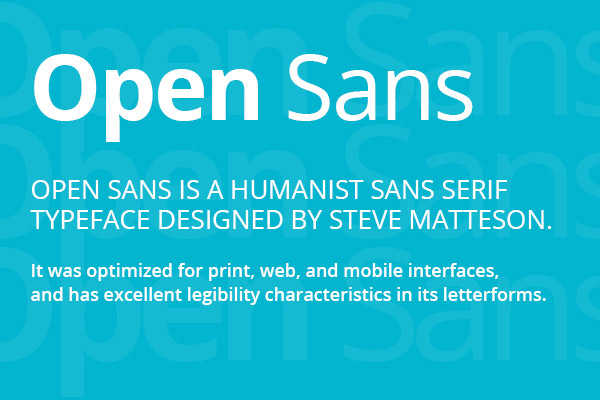
Font này được tại ra bởi Steve Matteson và nó có sẵn 10 biến thể. Phong cách đa dạng từ mỏng đến đặc biệt đậm nét. Font chữ khá đơn giản, gọn gàng và chuyên nghiệp.
Mặc dù font trông khá ổn khi ở kích cỡ to hơn hay nhỏ hơn nhưng tốt nhất hãy dùng nó ở dạng đặc biệt đậm là đẹp nhất.
Tôi muốn ám chỉ ở đây rằng phiên bản Open Sans Condensed cũng có sẵn ở 3 phong cách khác nhau. Toi nghĩ rằng phiên bản này có lẽ không phù hợp lắm với kích thước nhỏ, tuy vậy nhìn chung nó vẫn ổn với mọi trường hợp.
2. Oswald
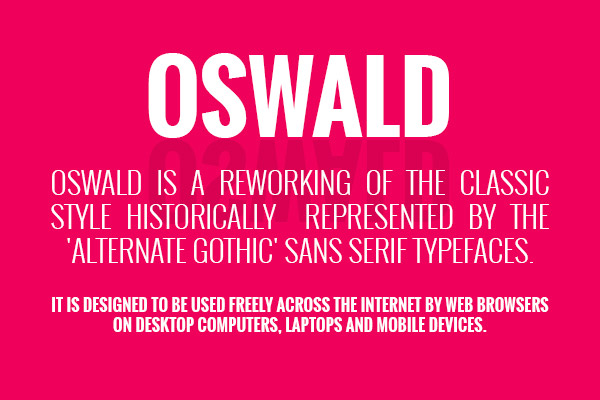
Oswald thuần túy là một font kỹ thuật số, nó đặc biệt được thiết kế để sử dụng cho các thiết kế web và thiết kế đồ họa trên mọi độ phân giải màn hình.
Đây là một phần của bộ font sans-serif, Oswald tiếp tục được cập nhật với các phiên bản được dùng trên website. Khoảng cách giữa các chữ nhỏ và nó rất hợp để làm chữ header.
Font chữ này nhìn khá gọn gàng cũng như hiển thị tốt trên các thiết bị duyệt web. Hãy cân nhắc đến việc dùng nó cho thiết kế web tiếp theo của bạn.
3. Lato
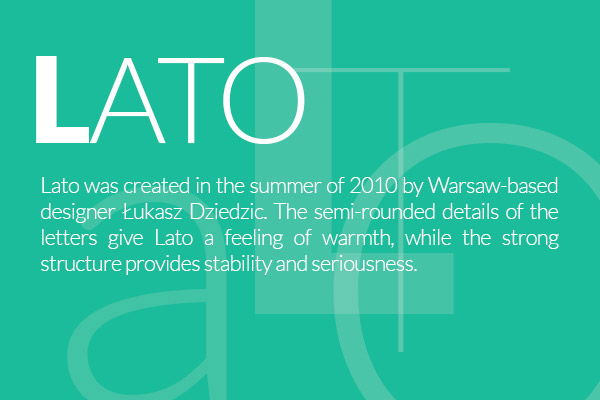
Lato vừa có vẻ đẹp vừa có sự mạnh mẽ, nó được ra mắt mùa hè năm 2010 bởi Łukasz Dziedzic.
Font cữ này đến từ bộ sans serif và được làm trong suốt một cách có chủ đích ở phần thân chữ. Những chi tiết nửa vòng tròn của chữ trông khá ấn tượng khi sử dụng cho responsive website. Đây là lựa chọn hoàn hảo cho dự án thiết kế web của bạn.
4. Arvo
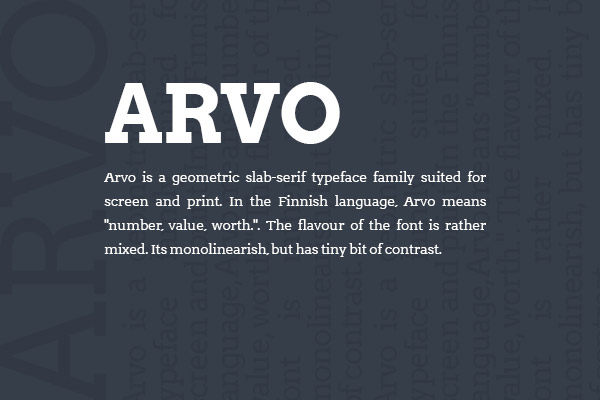
Arvo có nghĩa là số, giá trị, đáng giá theo tiếng Phần Lan. Nó thuộc bộ slab-serif với 4 kiểu: Roman, Italic, Roman Bold and Bold Italic.
Trông nó có vẻ góc cạnh xong lại có độ tương phản tốt và cảm giác ấm áp cho thiết kế. Font chữ linh hoạt này có thể sử dụng theo nhiều cách trong thiết kế. Bạn có thể nghĩ đến việc dùng nó cho các khổ chữ tiêu chuẩn, mang lại sự tương phản rõ ràng cho người đọc.